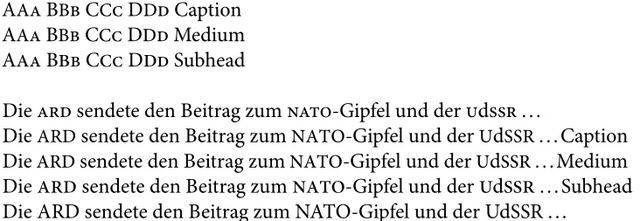
Kapitälchen in MinionPro
Meiner Ansicht nach entsprechen die Kapitälchen in MinionPro eher einer "Petite Caps" als einer "Small Caps" Variante, da die Kapitälchen nur geringfügig höher sind als die x-Höhe. Beim Setzen von Abkürzungen in Kapitälchen würde ich allerdings gerne auf eine höhere Kapitälchen-Variante zurückgreifen, da die momentane m.E. nicht so gut lesbar ist und Großbuchstaben zu sehr hervorstechen.
Da ich den Haupttext in MinionPro Regular 12 pt gesetzt habe, habe ich verschiedene Varianten versucht. Zum einen habe ich die Kapitälchen dickerer Schnitte (Caption, Medium) hochskaliert und zum anderen die Großbuchstaben von dünneren Schnitten (Subhead, Display) runterskaliert. Zusätzlich musste noch die Buchstabenabstände angepasst werden. Meiner Ansicht nach, eignet sich die Medium Variante. Nun wollte ich einmal eure Meinung zu dem Ergebnis hören. Sind diese falschen Kapitälchen akzeptabel oder sollte man besser darauf verzichten oder noch etwas anpassen?
Ich finde die Caps bei der Subhead-Variante etwas zu klein, aber bei der Medium teilweise zu mager.
@Schnitzel: Das die Subhead-Variante etwas kleiner ist als die Caption/Medium hat mich auch gestört. Wenn man sie jedoch weiter vergrößert, auf den gleichen Wert wie die Caption/Medium, wirkt sie m.E. recht fett. Ich habe sie jetzt in zwei Schritten vergrößert, um das zu veranschaulichen
• Subhead+ = Zwischenhöhe zwischen Caption und Subhead
• Subhead++ = gleiche Höhe wie Caption/Medium.
Die Medium zu verkleinern und sie dadurch fetter wirken zu lassen, ist natürlich möglich, aber dann hat man das schnell das gleiche Problem wie mit der Subhead Variante. Deswegen habe ich dies gar nicht erst versucht.